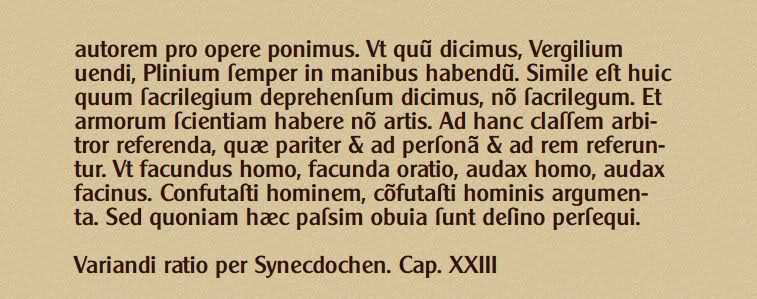
Die Schriftart kursiert unter den Namen “Cleaxg“, leider ohne jede Herkunftsangabe. Ich würde “Cleaxg” nehmen, allerdings ist mir der Glyphenvorrat zu gering. Welche Alternative kann man nehmen? Sie mutet halbfett an, mit kompakter Laufweite, serifenlos, allerdings ohne steril zu wirken, schon fast kalligraphisch, s. Abbildung.
@HansReichardt Du hast recht, mehr als nur ähnlich. Es sieht wie ein Ripp-Off aus, worauf auch der Name hinweist, clea… für Clearface und das “g” am Ende für “Gothic”.